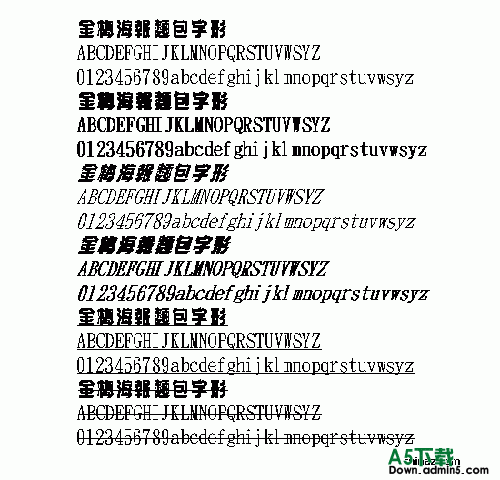
金梅海報(bào)面包字形(繁)
金梅海報(bào)面包字形(繁)是一個(gè)專門用來設(shè)計(jì)海報(bào)廣告的繁體字形,字體圓潤飽滿,需要的朋友快來綠色資源網(wǎng)里下載試試吧!
金梅海報(bào)面包字形是文鼎字體庫中一種字體,常用于美工設(shè)計(jì)方面,喜歡的朋友不要錯(cuò)過。